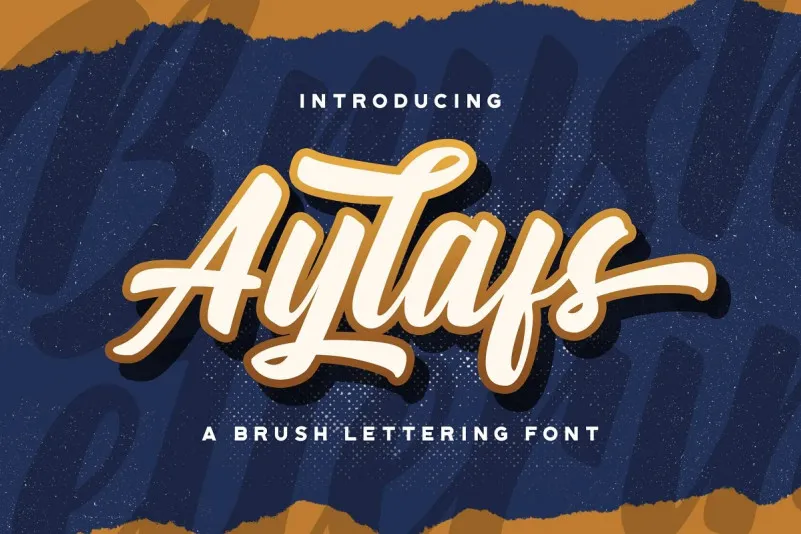
Aylafs Bold Script Font – Download Grátis
A Aylafs Bold Script Font é uma nova opção para aqueles que buscam beleza simples e elegância em seu design digital. Esta tipografia inspirada na calligrafia é perfeita tanto para elementos de layout quanto para gráficos digitais, garantindo um estilo único e duradouro. Simplesmente crie designs excepcionais com a Aylafs Bold Script Font, uma fonte de script bold que está à disposição para todos os seus projetos. E se você ainda não conhecia o designer 99designs antes, vale mencionar que ele é um dos maiores nomes no desenvolvimento de fontes digitais. Seja para trabalhos profissionais ou criatividades pessoais, a Aylafs Bold Script Font vai adicionar o toque final necessário ao seu projeto.